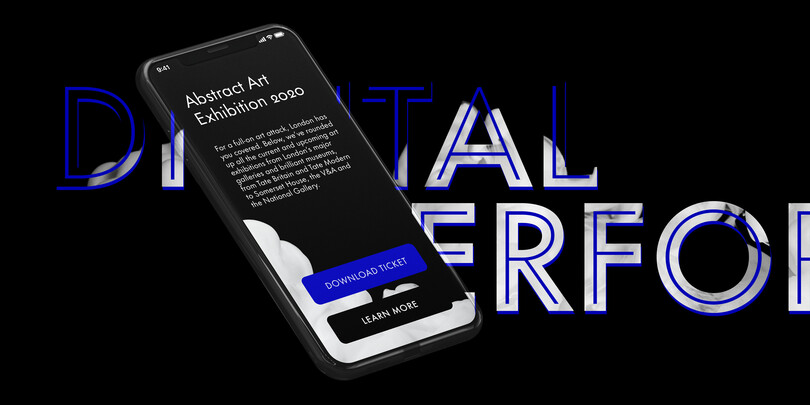
Die Futura des Jahrhunderts.
Es ist schwierig, sich das 20. Jahrhundert ohne Futura vorzustellen. Die von Paul Renner entworfene Schriftfamilie, 1927 bei der Bauerschen Gießerei in Frankfurt am Main erschienen, war schnell erfolgreich, inspirierte die Bauhaus-Bewegung und wurde eine Ikone der visuellen Kultur.
Futura ist zeitlos im reinsten Sinne, eine Art typografisches Chamäleon, das „in einem tropischen Baum genauso gut aussieht wie neben einem Stahltisch“, so beschreibt es Steve Matteson, Creative Type Director von Monotype.
Doch das 20. Jahrhundert liegt längst hinter uns. Die vom Druck dominierte Epoche, in der Futura weltweit aufblühte, wurde vom digitalen Zeitalter abgelöst, für das der Schriftklassiker schlecht gerüstet war. Ironischerweise ist das Design von Futura – anpassungsfähig, konsequent und von Nostalgie erfüllt – so populär und unverzichtbar wie eh und je, in vielerlei Hinsicht das perfekte ästhetische Gegengewicht zu unserer technikbesessenen Kultur.
Wie könnte eine Futura für das 21. Jahrhunderts aussehen? Sie müsste selbstverständlich für das Lesen am Bildschirm optimiert sein, vom überdimensionalen, hochauflösenden OLEDScreen bis hin zum Display einer Smartwatch. Sie böte sorgfältig gezeichnete Schnitte für jede Schriftgröße, unter besonderer Beachtung der Spationierung. Es gäbe sie als Variable Font, mit maximaler Flexibilität und der Fähigkeit, die (digitale) Typografie so perfekt wie nie zuvor zu dirigieren. Und sie müsste die gesamte Futura-Geschichte in sich tragen, einschließlich eigenwilliger Spielarten wie die Script- und Display-Schnitte.
Sie würde wie Futura Now gebaut sein.
Nie mehr fummeln.
„Der Clou von Futura Now ist: Du packst sie aus und kannst einfach loslegen“, sagt Terrance Weinzierl, der zum Designteam von Futura Now gehört. Das klingt vielleicht nicht nach einer großen Sache, doch frühere Versionen von Futura erforderten eine enorme „Fummelei“, wie Weinzierl es ausdrückt. Inkonsistente Abstände, eine beschränkte Zahl am Strichstärken, verzogene Italics und eine inkonsistente Sprachunterstützung limitierten den Einsatz von Futura für moderne digitale Marken. „Ohne jemandem zu nahe treten zu wollen … werfen Sie einfach mal einen Blick auf unsere Linotype-Futura, dann werden Sie schnell erkennen, wie beliebig die Familie zusammengestellt ist“, sagt Wienzierl. „Man braucht viel Erfahrung, um mit dieser Version zu arbeiten.“
Eine Maßnahme zur Benutzerfreundlichkeit von Futura Now ist die Einführung optischer Größen: Futura Now Text und Futura Now Headline. Während optische Größen in vielen Fällen, vor allem bei Serifenschriften, durch das Anpassen von Buchstabenformen entstehen, die das Lesen bei bestimmten Punktgrößen und Betrachtungsabständen verbessern, zielten die optischen Größen von Futura Now einzig auf die Beseitigung der oben erwähnten Spationierungsprobleme ab.
Wie der Name vermuten lässt, ist Futura Now Text „luftiger“ zugerichtet, um das Lesen von Mengentext angenehm zu machen. Ihre klassischen Buchstabenformen haben sowohl auf Papier als auch am Bildschirm ausreichend „Platz zum Atmen“. Dies macht sich vor allem bei den leichteren Schnitten bemerkbar, wo mehr Weißraum den feinen Linien erlaubt, sich zu entfalten. Futura Now Headline läuft etwas enger, was einerseits dem begrenzten Platz für Überschriften entgegenkommt, aber auch die visuelle Wucht erzeugt, die Futura bei Werbern und Künstlern gleichermaßen beliebt gemacht hat.
„Das Spationieren ist so wichtig im Typedesign“, betont Juan Villanueva, Schriftentwerfer bei Monotype, der ebenfalls an Futura Now mitgewirkt hat. „Das Hinzufügen von etwas mehr Raum kann auf Anhieb zu einer besser lesbaren Schrift über mehrere Textgrößen führen“.
Während diese Anpassungen schon immer für den Druck sinnvoll waren, machen sie sich im digitalen Umfeld noch viel mehr bemerkbar. „Die Bildschirmqualität von Texten nähert sich der auf Papier“, sagt Weinzierl. „1995 waren die Bildschirme so grob, dass optische Größen keinen Effekt gezeigt hätten, wenn es sie gegeben hätte“, ergänzt Weinzierl. „Heute tragen wir 400-dpi-Bildschirme am Handgelenk. Wir haben so viel mehr Pixel, mit denen wir arbeiten können.“ Die optischen Größen nutzen diese Pixeldichte voll aus und sorgt für eine makellose Lesbarkeit in jeder digitalen Umgebung.
Juan Villanueva, Monotype Type Designer.
Mit Futura Now kommen auch zum ersten Mal Variable-FontVersionen der Schrift auf den Markt, in den drei Unterfamilien Text/Headline (zusammengefasst), Display und Script. Variable Fonts werden manchmal separat oder als Ergänzung zu statischen Fonts entwickelt, doch Futura Now wurde „variabel geboren“, sagt Weinzierl und ergänzt, dass die variablen Versionen zuerst entwickelt und die statischen Fassungen daraus extrahiert wurden.
Jeder Variable Font stellt entlang einer Designachse (zum Beispiel Strichstärke) eine schier endlose Zahl von Zwischenstufen bereit. Zwecks leichter Bedienbarkeit hat das Studio, wie Wienzierl und Villanueva erläutern, „Lesezeichen“ eingebaut, die wie eine Preset-Taste am Radio funktionieren und bei den statischen Schnitten einrasten. Für die Benutzer bedeutet dies, dass sie Futura Now hochfein einstellen können, aber auch schnell wieder den Weg zurück zu einer von den Brand-Guidelines geforderten Schnitt finden, indem sie einfach den vertrauten Stilnamen im Schriftmenü wählen.
Da sich Marken zunehmend für die digitale Zukunft rüsten, werden Techniken wie optische Größen und Variable Fonts dazu beitragen, den Kunden ein einheitliches visuelles Erlebnis zu bieten, ganz gleich, ob sie der Marke am Smartphone, dem Tablet, am Laptop oder auf der Watch begegnen. „Bei der Skalierbarkeit geht es nicht mehr nur um die Größe des Texts, sondern auch um den Betrachtungsabstand“, betont Weinzierl. „Bei einem Smartphone beträgt er vielleicht 15 bis 20 cm, am Schreibtisch könnten es 50 bis 80 cm sein. Man braucht heute Schriften, die auf all diese Lesesituationen flexibel reagieren, ohne Abstriche bei der Markenkonsistenz.”
„Wir haben das komplette Futura-Universum studiert, es bereinigt und so geordnet, das es die Schriftbenutzer von heute sofort verstehen“, sagt Villanueva. „Wir haben uns ständig gefragt: Was braucht diese Familie, um aktuell zu sein? Wie sieht die beste Version von Futura für die nächsten fünfzig oder hundert Jahre aus? Das ist es, was wir schaffen wollten.“